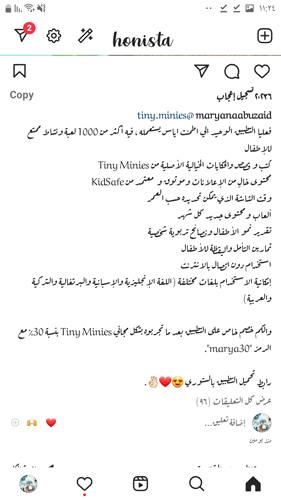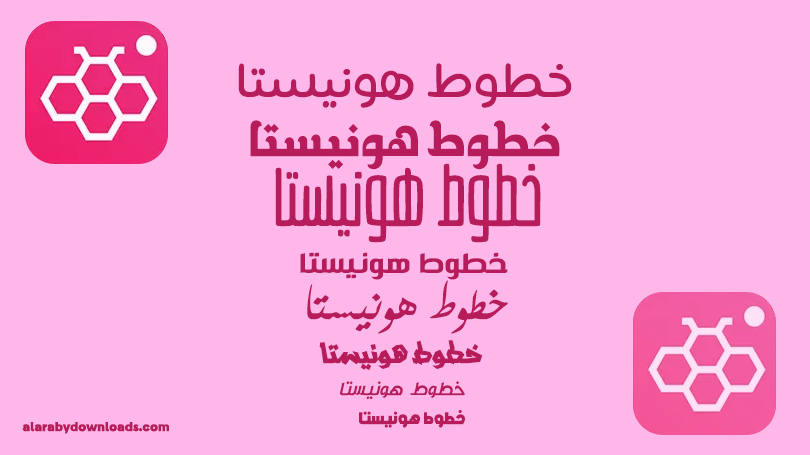
تحميل خطوط ايفون هونيستا Honista iOS Fonts
خطوط ايفون هونيستا ttf
تطبيق هونيستا أو خطوط ايفون هونيستا هي عبارة عن مجموعة واسعة من الخطوط الأنيقة والحديثة، يمكنك تخصيص تجربة انستقرام الخاصة بك وجعلها مميزة عن باقي المستخدمين، من خلال خطوط مخصصة تم تصميمها لتتوافق مع تطبيق انستقرام، حيث تجد الكثير من الخطوط المميزة التي تشد انتباهك في تطبيق هونيستا، وهذا ما لا تجده في تطبيق انستقرام بلس، أو حتى انستقرام الأصلي لا يوفر لك مجال لتغيير الخطوط أو التحكم بها، أما في تطبيق هونيستا تجد أمامك خطوط هونيستا ايفون، والتي تجعلك تشعر كانك تستخدم جهاز ايفون من خلال الخطوط المميزة، تابع معنا التفاصيل أكثر وتعرف على طريقة تحميل خطوط ايفون هونيستا للاندرويد.
خطوط ايفون هونيستا
أسرار حول خطوط هونيستا
خط ايفون عريض هونستا
ربما يكون هذا النوع من الخطوط هو الأكثر طلبًا وانتشارا بين أنواع الخطوط التي يقدمها تطبيق هونيستا للايفون، حيث تجعل الخطوط التي يوفرها خطوط ايفون هونيستا مجانا، تستطيع استخدام خط ايفون عربي بكل سهولة في تصاميم الصور والفيديوهات والستوريات، اختر خط ايفون هونيستا المناسب لك وتمتع باستخدامه.
ما الجديد في تحديث خطوط هونيستا للايفون